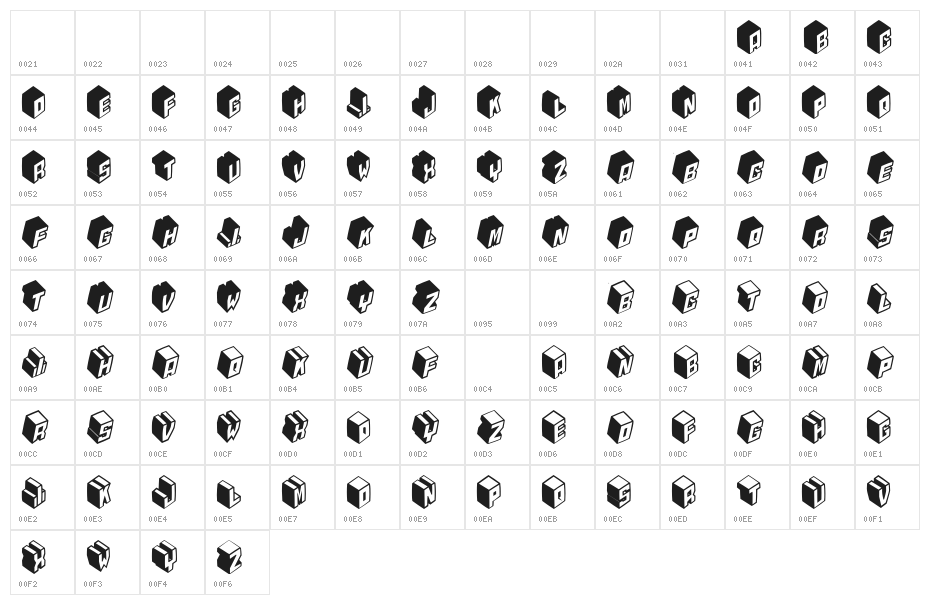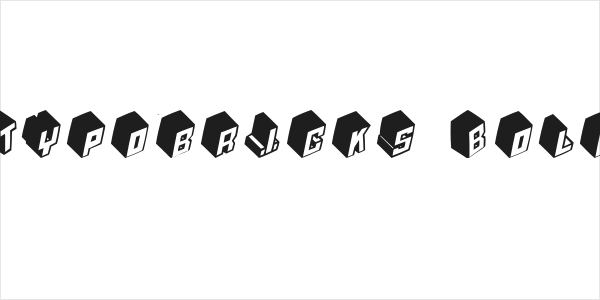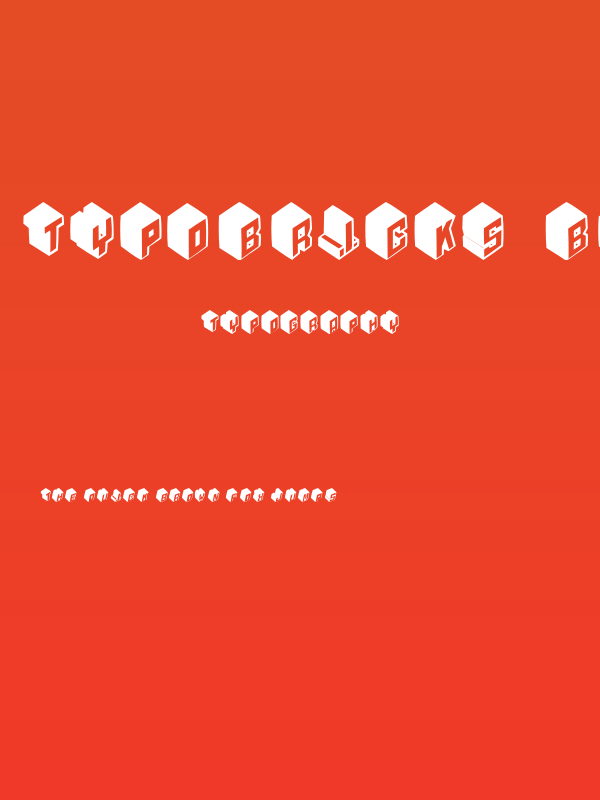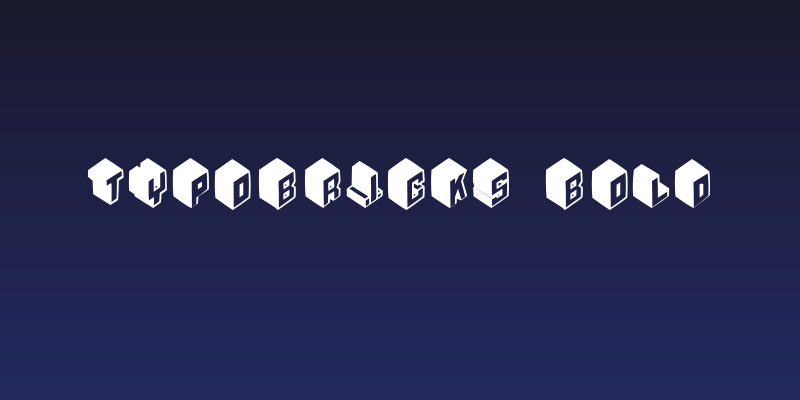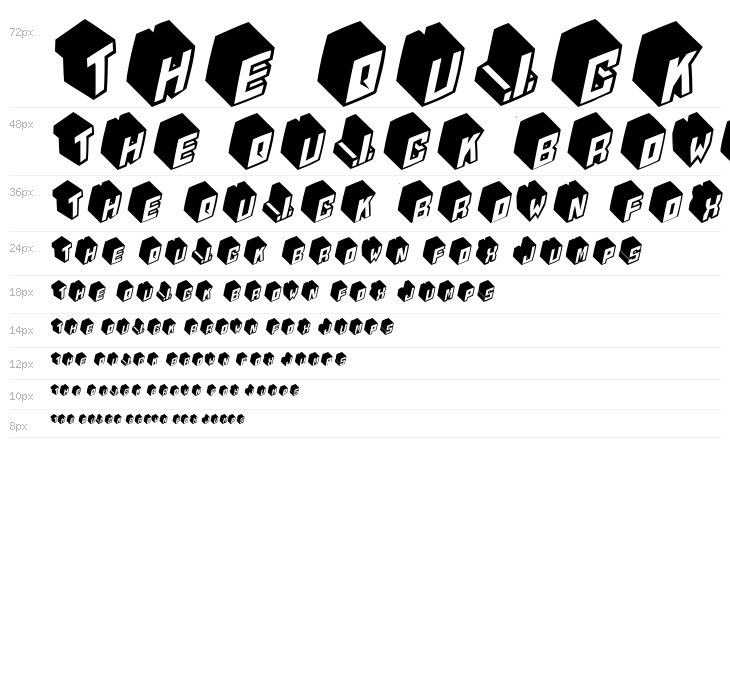
Typobricks-Bold Font
TYPOBRICKS-BOLD MAIUSCOLE
TYPOBRICKS-BOLD MINUSCOLO
TYPOBRICKS-BOLD ALTRI CARATTERI
| Progetti proposti | Ideal for construction-themed posters, architectural branding, children's educational materials, or any project requiring a playful yet structured look. |